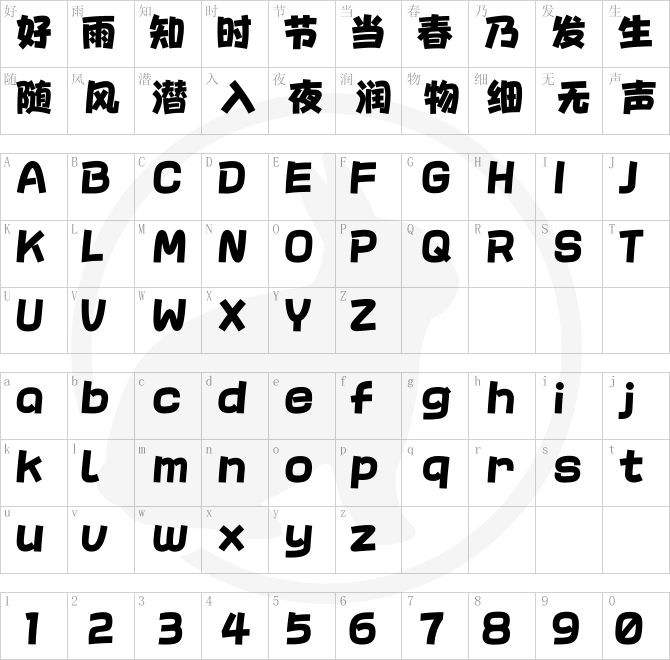
Aa圆黑体
Aa圆黑体,这款字体结构工整、笔画清晰,兼顾美观与易读性,适用于标题、正文、海报、包装、LOGO 等多种场景。字形优雅稳定,风格百搭耐看,适配日常排版与创意设计,让文字呈现更舒适、更具质感。Aa圆黑体一笔一画,皆是细节,以均衡的比例、流畅的线条打造舒适视觉体验,字形端正大气,风格简约现代。无论是商业设计、品牌宣传还是日常排版,都能轻松驾驭,让文字更有格调与力量。Aa圆黑体字体下载。